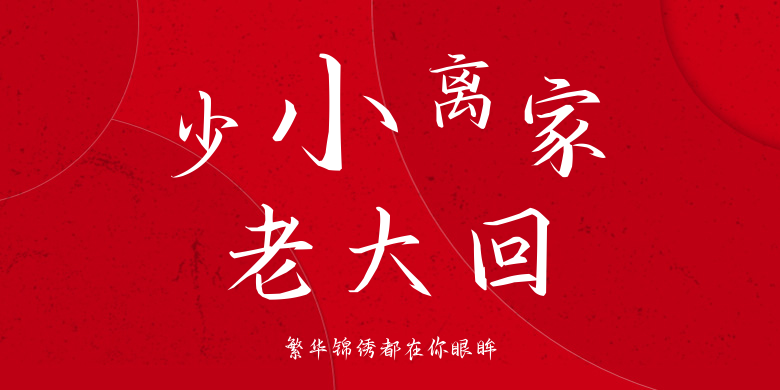
繁华锦绣都在你眼眸
繁华锦绣都在你眼眸,这款字体结构工整、笔画清晰,兼顾美观与易读性,适用于标题、正文、海报、包装、LOGO 等多种场景。字形优雅稳定,风格百搭耐看,适配日常排版与创意设计,让文字呈现更舒适、更具质感。繁华锦绣都在你眼眸一笔一画,皆是细节,以均衡的比例、流畅的线条打造舒适视觉体验,字形端正大气,风格简约现代。无论是商业设计、品牌宣传还是日常排版,都能轻松驾驭,让文字更有格调与力量。繁华锦绣都在你眼眸字体下载。